Việc chọn phông chữ TikTok phù hợp có khiến video của bạn trở nên lan truyền rộng rãi hơn không? Câu trả lời sẽ là không. Nhưng giống như bất kỳ quyết định thiết kế nào khác, phông chữ có thể tạo ra tác động cho người xem mà bạn muốn hướng đến. Do đó, bài viết dưới đây sẽ hướng dẫn bạn cách lựa chọn font chữ phù hợp. Đồng thời, hướng dẫn cách thêm chữ vào video TikTok.
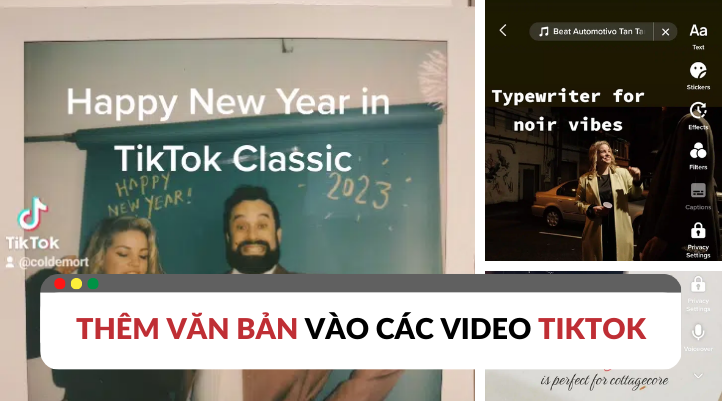
Phông chữ của TikTok là gì?
Phông chữ TikTok là các kiểu chữ có sẵn trong ứng dụng. Bạn có thể chọn giữa các phông chữ như: Cổ điển, Máy đánh chữ, Neon và Serif khi thêm chữ vào video hoặc ảnh TikTok.
Cổ điển
Cổ điển là phông chữ đơn giản và sạch sẽ. Đây cũng là phông chữ rất được ưa chuộng để thêm vào các video TikTok.
Phông chữ cổ điển của TikTok trông rất giống Proxima Nova. Một phông chữ vẫn còn phổ biến ở khắp mọi nơi vào đầu những năm 2000. Đó là kiểu chữ chính cho nhiều công ty trực tuyến, như BuzzFeed, Mashable, NBC News và Wired.
Phông chữ này sẽ không làm bạn mất tập trung vào nội dung. Vì vậy nó có thể là lựa chọn phù hợp cho bất kỳ bản sao nội dung nào trong video của bạn. Nó cũng giúp bạn dễ dàng đọc các video hướng dẫn hoặc đồ họa thông tin.
Máy đánh chữ
Máy đánh chữ mang lại cảm giác ghoài cổ chủ yếu của những năm 1950. Cảm giác cổ điển của máy đánh chữ làm cho nó trở nên hoàn hảo cho nội dung hồi tưởng hoặc cổ điển, nhưng nó cũng rất phù hợp cho các bài viết thơ mộng hoặc thơ mộng hơn.
Chữ viết tay
Phông chữ chữ viết tay của TikTok nghiêng về phía nữ tính hơn. Vì vậy, phông chữ này rất phù hợp cho những người tạo nội dung làm đẹp hoặc thời trang. Mặc dù đẹp, nhưng phông chữ này có thể khó đọc. Nó hoạt động tốt nhất dưới dạng tiêu đề, tiêu đề hoặc để nhấn mạnh.
Phông chữ neon
Hình học, tươi sáng và nổi bật, Neon mang hơi hướng nghệ thuật nhẹ. Phông chữ này được thiết kế để nổi bật, vì vậy đừng để nó cạnh tranh với chính nó. Phông chữ Neon có thể đứng một mình.
Bạn cũng không nên sử dụng nó để viết những đoạn văn dài. Một đến ba từ là đủ.
Không giống như các lựa chọn phông chữ khá hạn chế của TikTok. Việc sử dụng một công cụ bên ngoài sẽ mở ra cả một thế giới các ký tự lạ mắt mà bạn có thể thêm vào nội dung của mình. Ngay cả khi bạn tạo video trong ứng dụng của bên thứ ba, bạn vẫn có thể sử dụng phông chữ của TikTok.